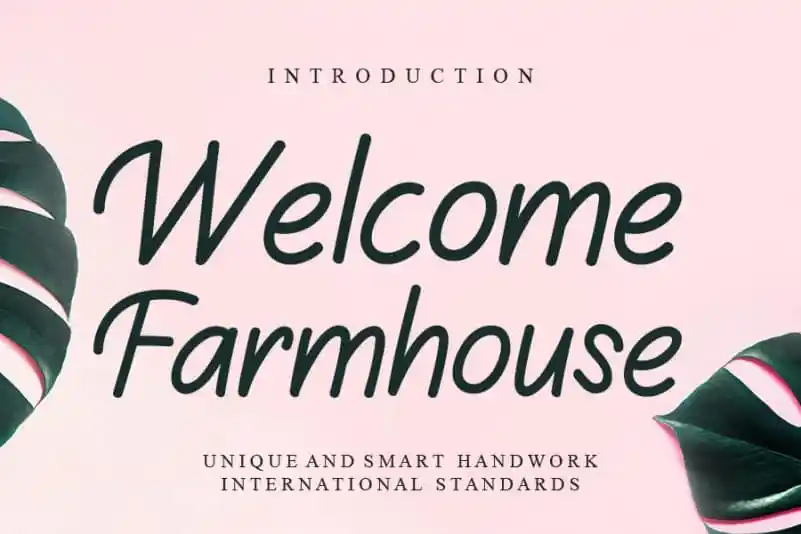
Welcome Farmhouse Handwritten Font – Fonte Grátis
Welcome Farmhouse Handwritten Font
A fonte “Welcome Farmhouse Handwritten Font” é uma delicia para quem aprecia a simplicidade e amabilidade do estilo farmhouse na tipografia. Criada pelo designer creativeletter, essa fonte oferece um toque acolhedor e natural que se assemelha a desenhos feitos à mão. Seja em gráficos de decoração ou em elementos digitais do dia-a-dia, sua textura única é perfeita para criar uma atmosfera confortável e descontraída. Trazendo um leve toque vintage ao seu trabalho visual, esta fonte se destaca pela sua personalidade sóbria, dando vida a mensagens pessoais e memoráveis. Não há como errar em uma fonte que traz a essência do estilo farmhouse para o mundo digital. Aproveite o design cuidadoso desta fonte escrita à mão, criada para dar um toque especial aos seus projetos digitais.